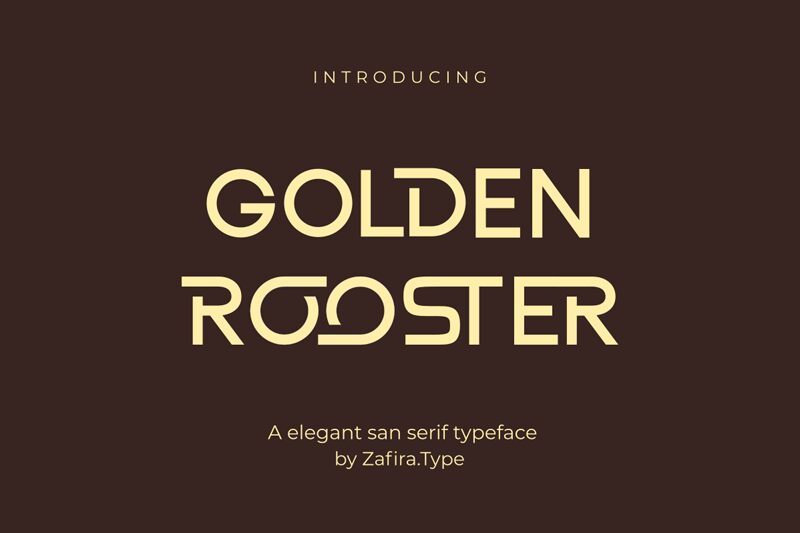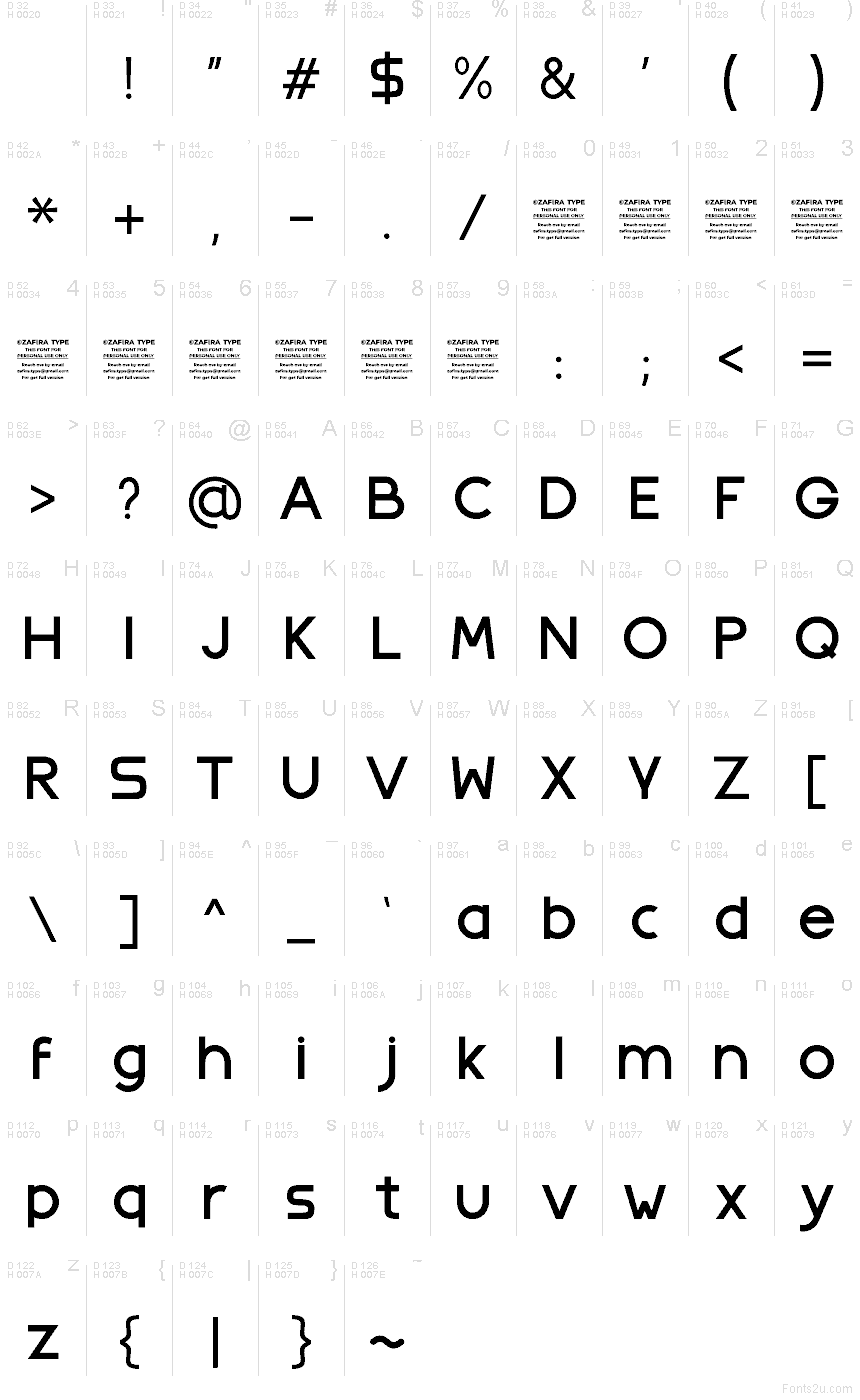
Golden Rooster
Golden Rooster von Zafira.Type ist eine kostenlose serifenlose Schrift mit abgerundeten, geometrischen Buchstabenformen und sanften, gleichmäßigen Kurven. Die Gestaltung wirkt ausgewogen und direkt, mit offenen Punzen und einer klaren Struktur, die das Design ohne unnötige Verzierungen präzise hält.
Golden Rooster eignet sich hervorragend für Logodesigns, Verpackungen, kurze redaktionelle Überschriften, Produktetiketten, Poster und Akzente auf Websites, bei denen eine schlichte serifenlose Schrift gefragt ist. Dieses kostenlose Font verleiht Texten einen ruhigen, klaren Rhythmus und gibt Branding- oder Layout-Elementen eine unaufdringliche, gelassene Präsenz.